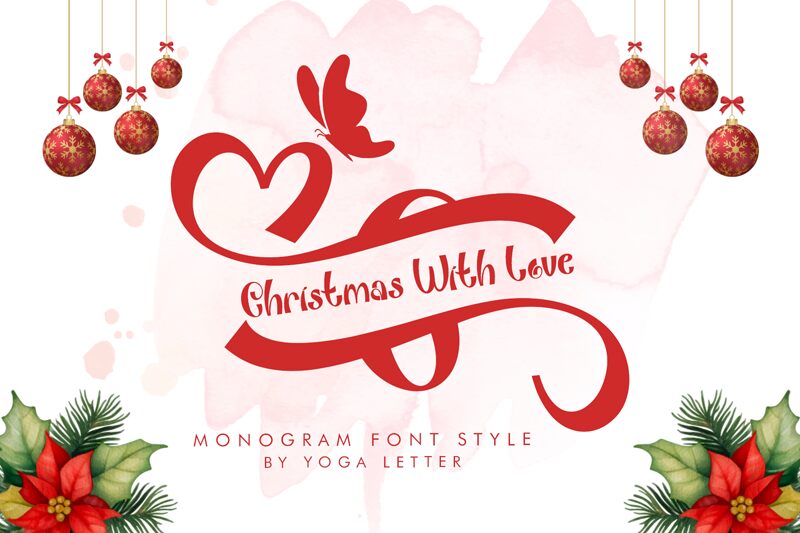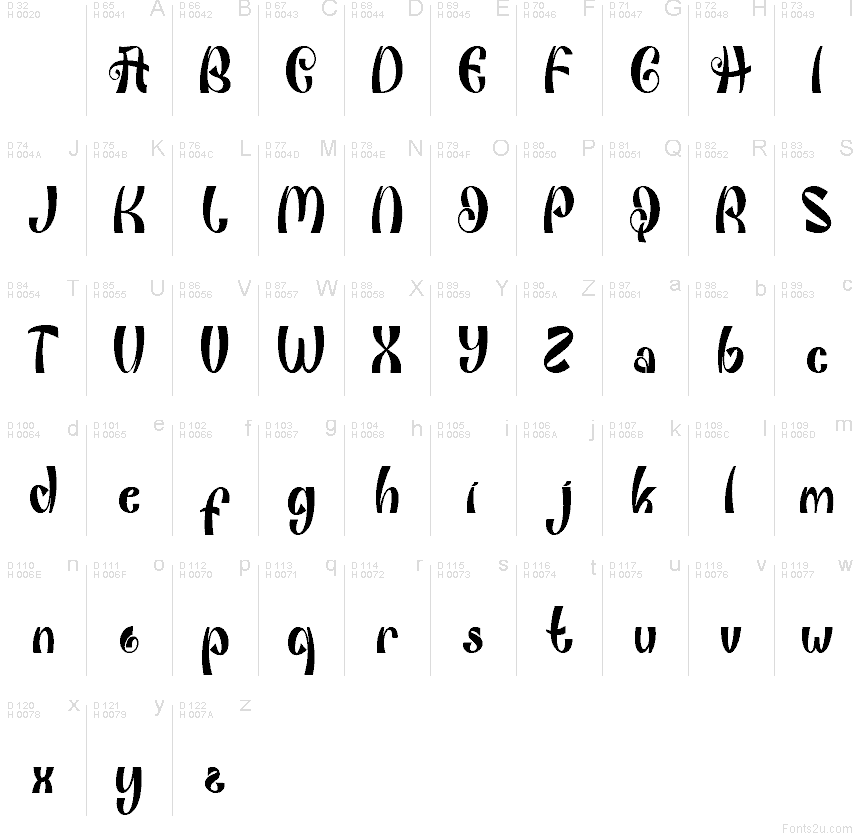
Christmas With Love Demo
Christmas With Love de Yoga Letter es una tipografía script gratuita con trazos fluidos y una elegante forma manuscrita. Sus letras se entrelazan mediante bucles elevados y formas estrechas, logrando un ritmo festivo y formal que aporta un toque refinado a cualquier diseño navideño.
Esta fuente es ideal para tarjetas de felicitación, etiquetas de regalo, títulos de invitaciones, logotipos de temporada, arte mural y gráficos festivos para redes sociales. Su trazo caligráfico y movimiento decorativo son perfectos cuando buscas un estilo personal y festivo sin sacrificar una estructura elegante.